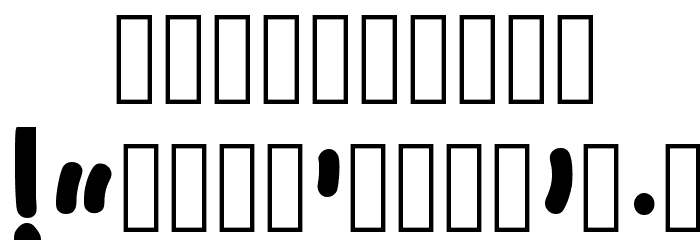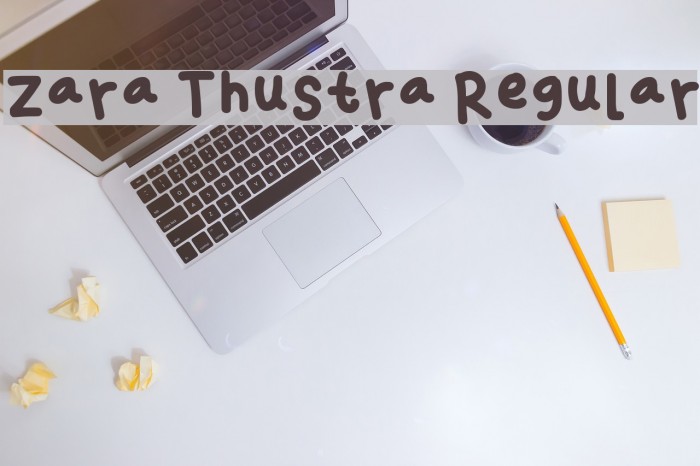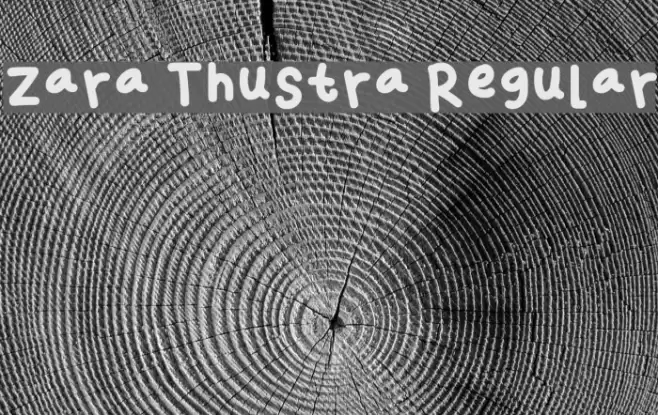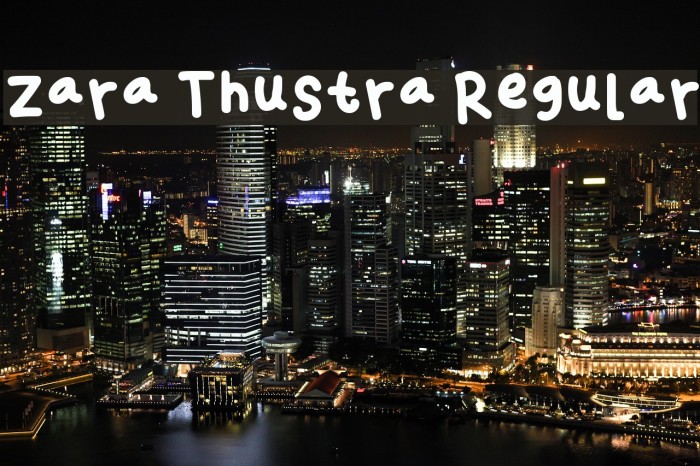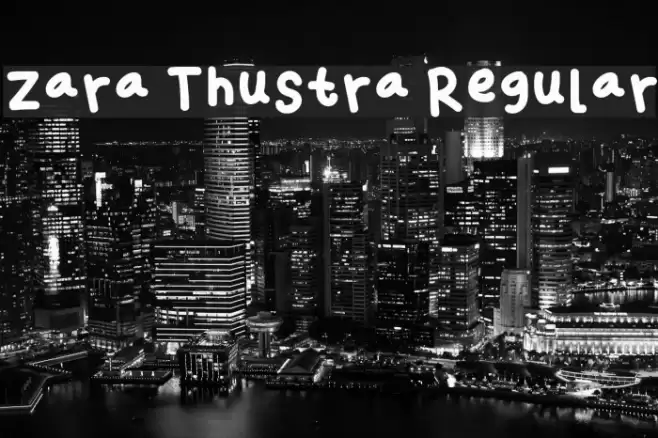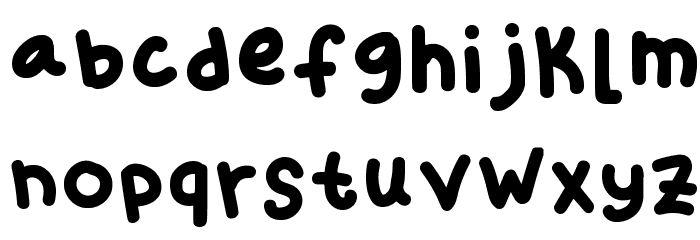
Zara Thustra Regular Font
| Caso d'uso | Headlines, Logos, Casual Text |
| Progetti proposti | Ideal for children's books, greeting cards, playful branding, and casual invitations. |